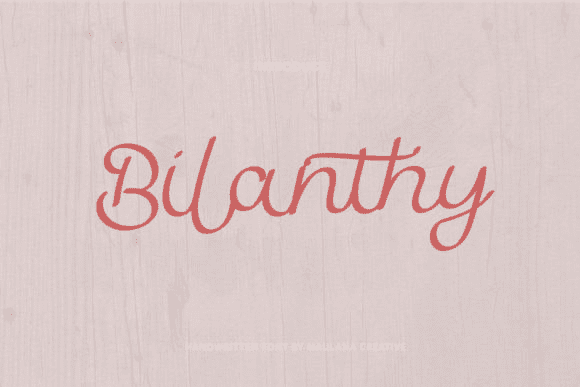
Название: Bilanthy Font
Благотворительность - это тонкий и скорописный шрифт, написанный от руки.
Этот нежный шрифт будет великолепно смотреться на разнообразных дизайнерских идеях.
Он добавит в каждый из ваших проектов радостный и романтичный штрих!
Название: Bilanthy Font
Благотворительность - это тонкий и скорописный шрифт, написанный от руки.
Этот нежный шрифт будет великолепно смотреться на разнообразных дизайнерских идеях.
Он добавит в каждый из ваших проектов радостный и романтичный штрих!